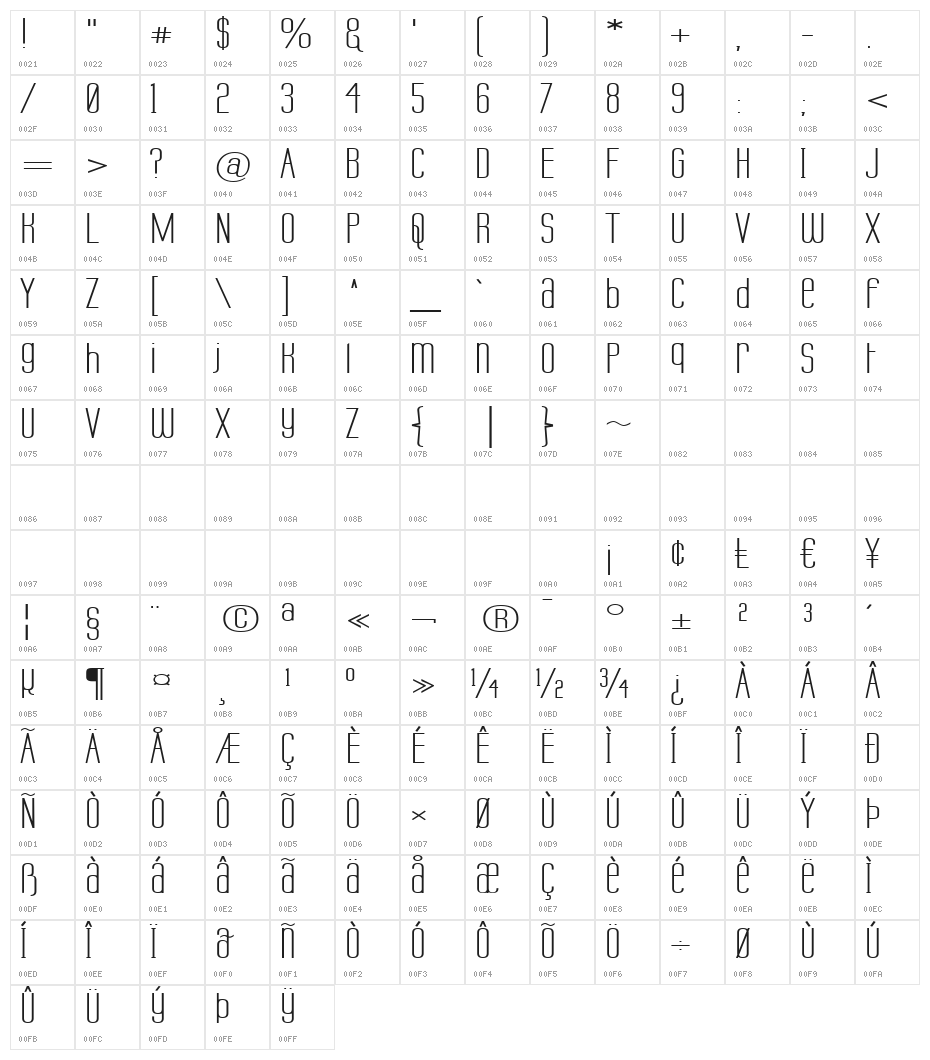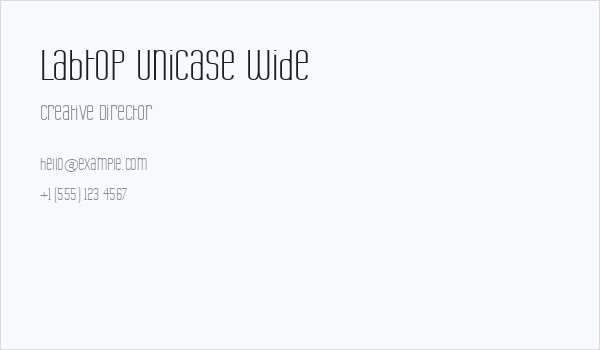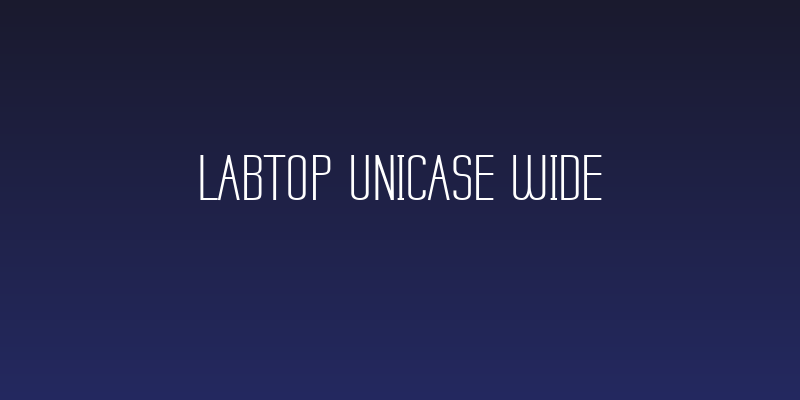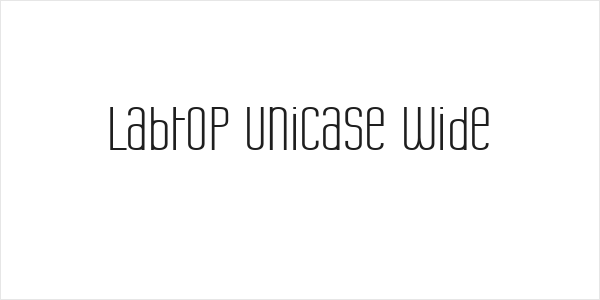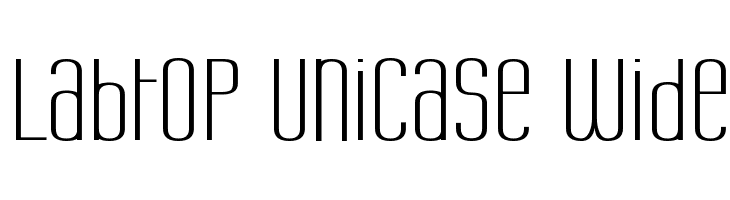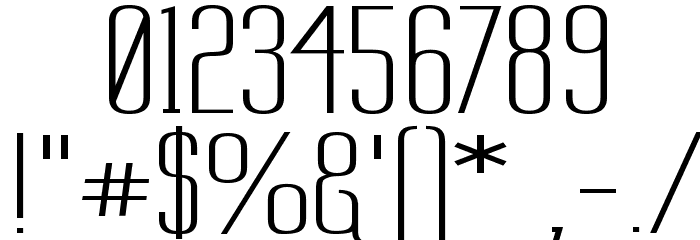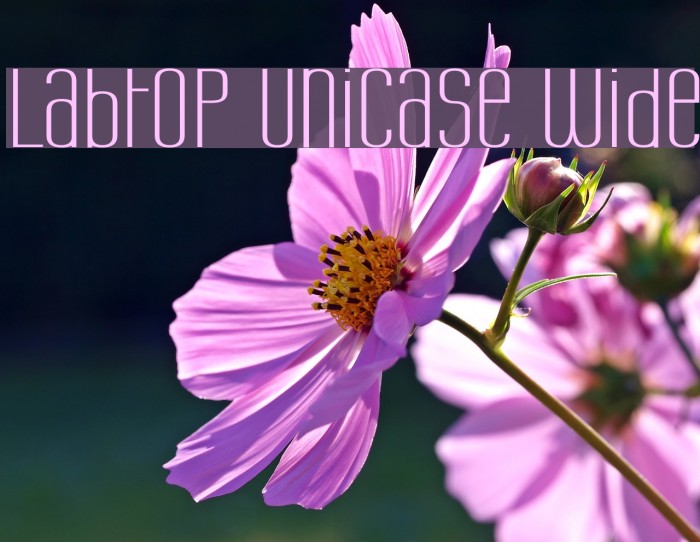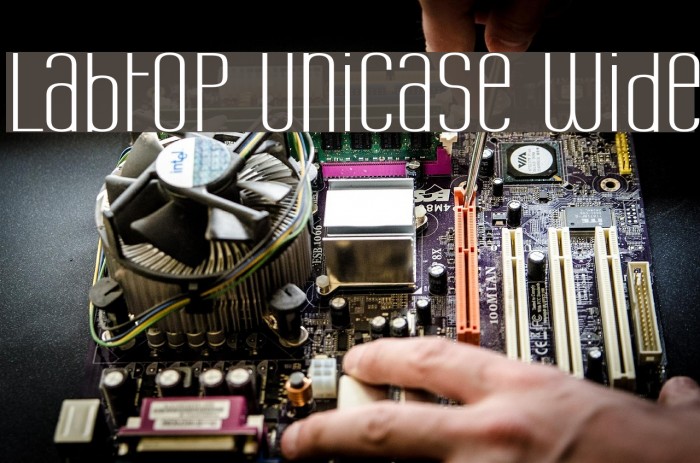
Labtop Unicase Wide Font
| Proiecte propuse | Ideal for branding, advertising, posters, and digital media where a modern and sleek appearance is desired. |